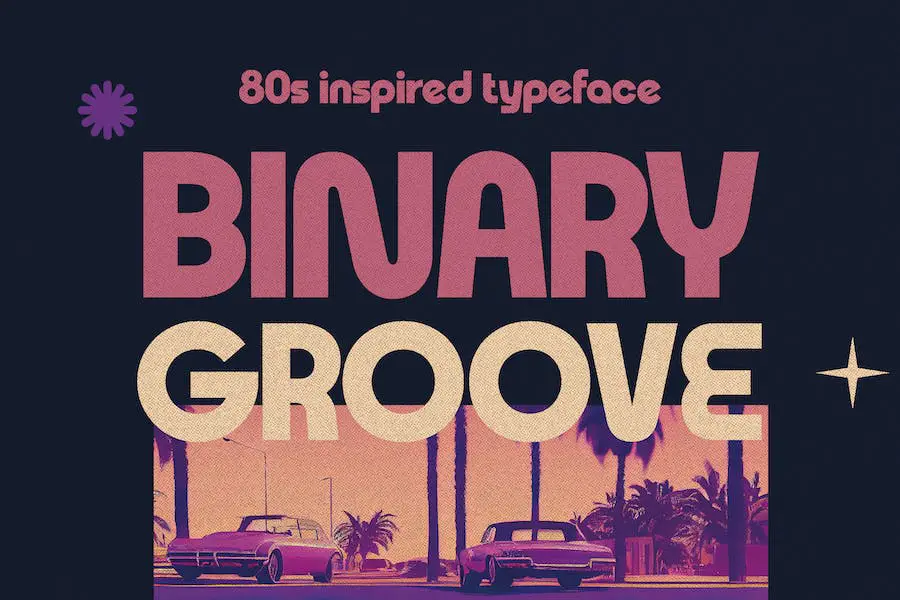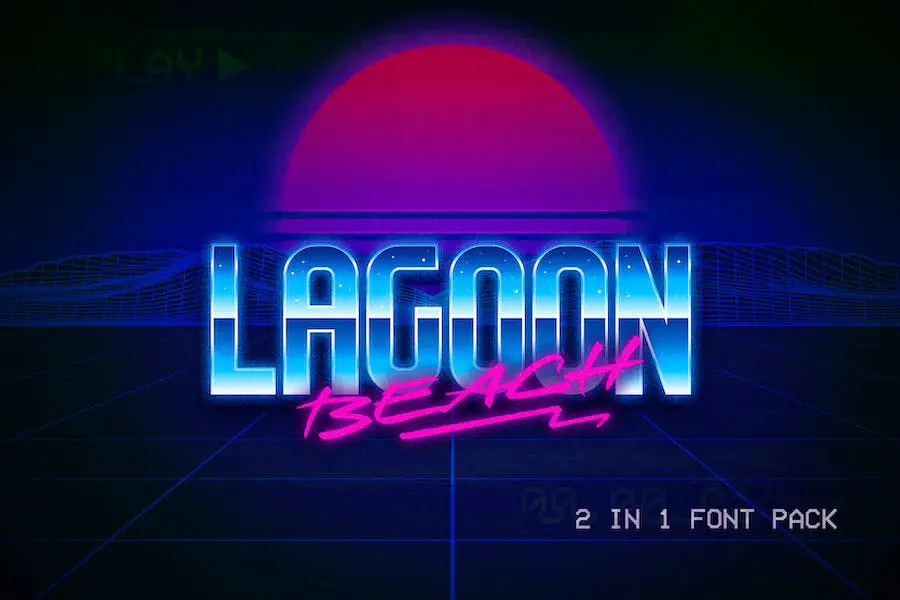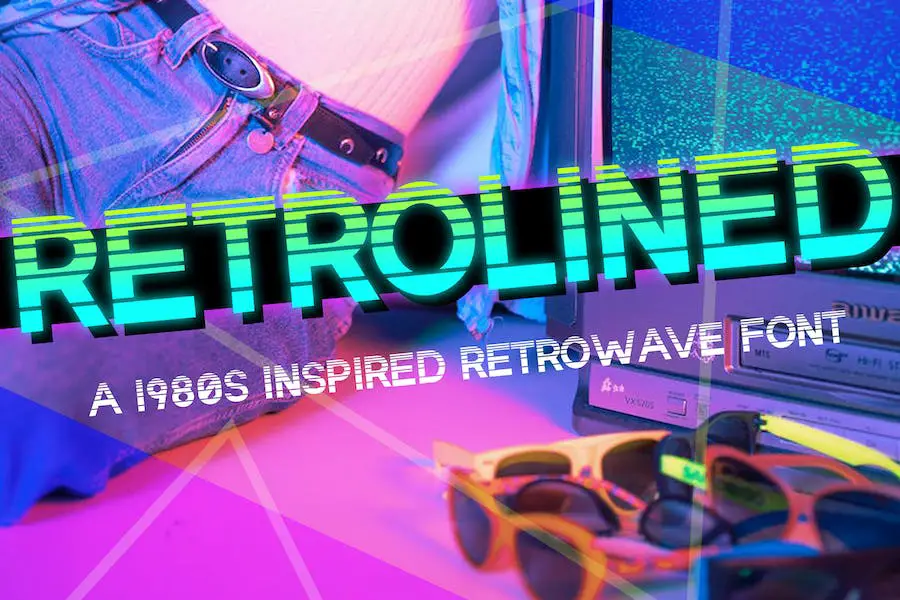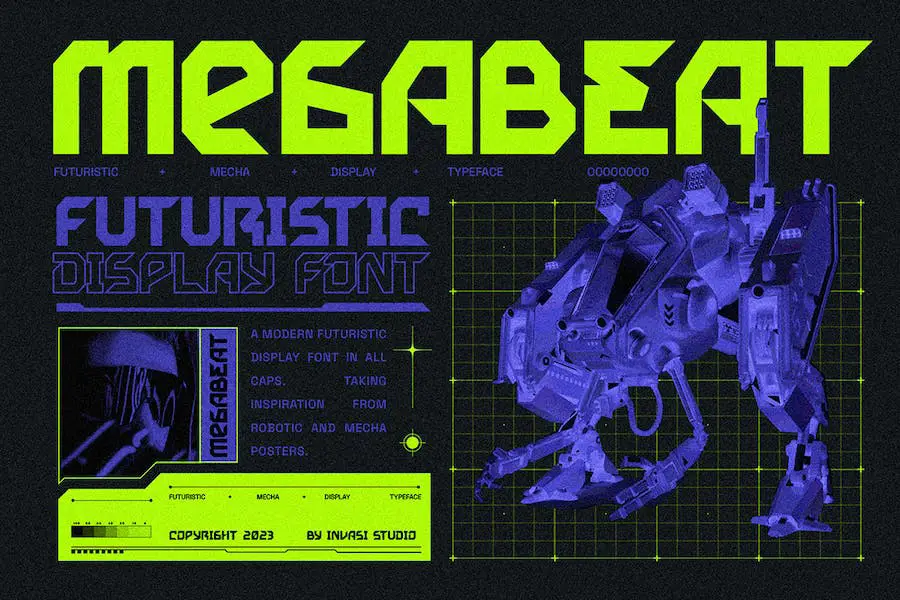
2023년 최고의 Vaporwave 글꼴 20개(무료 및 프리미엄)
게시 됨: 2023-09-06어떤 종류의 글꼴이 그래픽 디자인 프로젝트를 한 단계 더 발전시킬 수 있는지 궁금한 적이 있습니까? 더 이상 보지 마세요! 이 블로그 게시물에서는 프로젝트 디자인을 즉시 향상시킬 수 있는 최고의 증기파 글꼴 20가지를 살펴보겠습니다.
증기파란 정확히 무엇입니까? 베이퍼웨이브는 향수를 불러일으키는 80년대와 90년대의 미학으로 유명한 2010년대 초반에 시작된 음악 및 예술 장르입니다.
Vaporwave 글꼴은 대담하고 생생한 색상과 미래 지향적인 디자인으로 이 독특한 예술 형식의 본질을 포착합니다. 로고, 포스터, 웹사이트 등 어떤 작업을 하든 이러한 글꼴을 통합하면 프로젝트에 복고풍이면서도 현대적인 느낌을 줄 수 있습니다.
이제 증기파 글꼴의 세계로 뛰어들어 디자인을 변화시킬 상위 20가지 옵션을 살펴보겠습니다. 대담하고 기하학적인 글꼴부터 기발하고 몽환적인 글꼴까지 가장 인기 있고 시각적으로 매력적인 글꼴 목록을 선별했습니다.
이제 더 이상 고민하지 말고 여러분의 디자인 프로젝트를 다른 사람들보다 돋보이게 만들어 줄 글꼴을 찾아보세요.
최고의 프리미엄 Vaporwave 글꼴
그래픽 디자인 프로젝트를 향상시키고 싶으십니까? 우리가 엄선한 최고의 프리미엄 Vaporwave 글꼴 컬렉션을 만나보세요. 이 글꼴은 디자인에 독특하고 복고풍의 미학을 더해 다른 사람들보다 눈에 띄게 만들어줍니다.
최고의 글꼴을 탐색하고 실험할 수 있는 기회를 놓치지 마십시오. 귀하의 프로젝트를 한 단계 더 발전시켜줄 것입니다.
레트로퓨처리즘
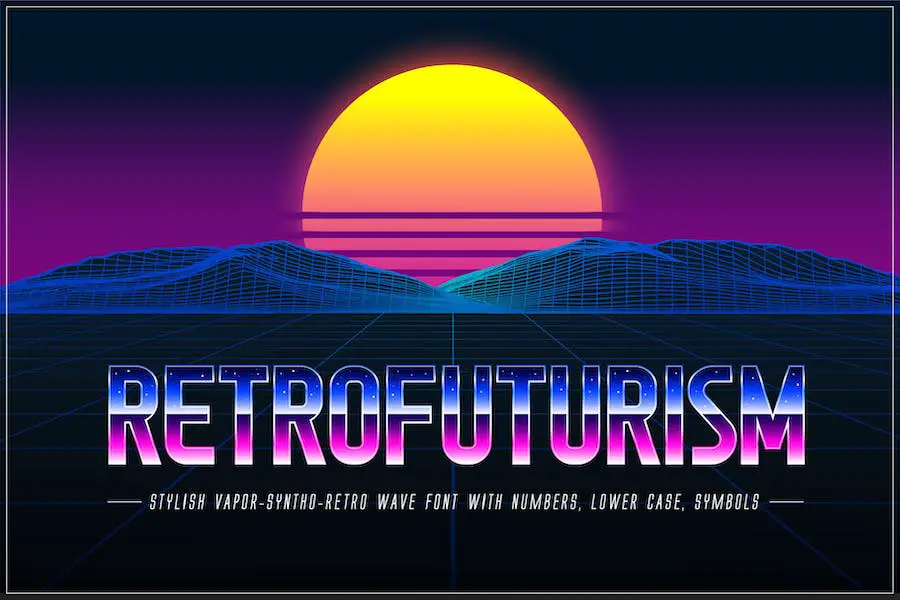
Retrofuturism은 Vaporwave, Synthwave 및 Retrowave 스타일의 복고풍 미래 지향적인 분위기를 프로젝트에 제공하는 멋지고 트렌디한 글꼴입니다.
독특하고 눈길을 사로잡는 미학을 갖춘 Retrofuturism은 향수와 미래 지향적인 감각으로 프로젝트를 향상시키려는 그래픽 디자이너에게 완벽한 선택입니다.
이 글꼴은 매우 다재다능하며 복고풍에서 영감을 받은 로고 및 브랜딩 제작부터 눈길을 끄는 포스터 및 소셜 미디어 그래픽 디자인에 이르기까지 다양한 디자인 목적으로 사용할 수 있습니다.
대담하고 역동적인 외관은 텍스트를 돋보이게 하고 시선을 사로잡아 디자인에 즉시 멋지고 복고풍적인 분위기를 더해줍니다.
증기미래주의
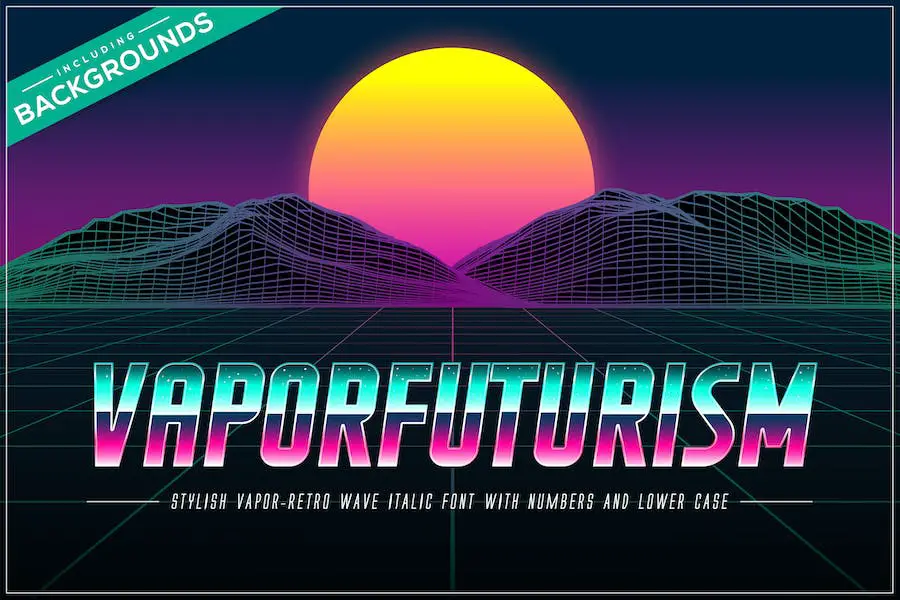
Vaporfuturism은 트렌디한 Vaporwave, Synthwave 및 Retrowave 스타일을 디자인에 적용하는 환상적인 글꼴 팩입니다.
하지만 그게 다가 아닙니다. 이 팩에는 추가 증기파 배경 4개와 샘플 전단지 2개가 포함되어 있습니다. 마치 하나의 패키지에 미니 디자인 키트가 들어있는 느낌이에요! 이러한 요소를 프로젝트에 통합하여 전반적인 미적 특성을 강화하고 눈에 띄게 만들 수 있습니다.
비디오 카세트
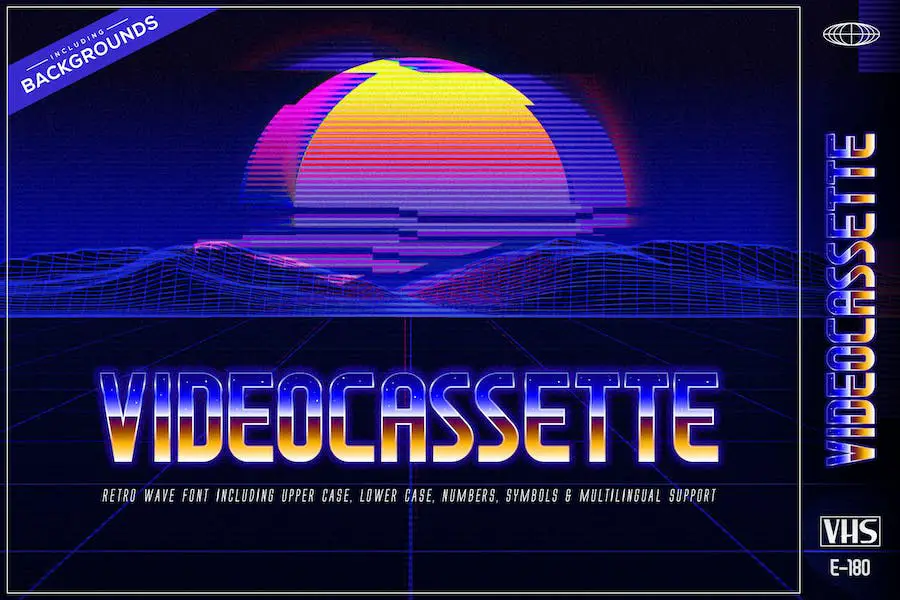
Videocassette는 팩에 포함된 80년대 Vaporwave 글꼴로 트렌디한 Vapor Wave, Synth Wave, Retro Wave 스타일이 특징입니다.
포스터, 앨범 표지, 웹사이트 디자인 등 어떤 작업을 하든 이 글꼴은 독특하고 눈길을 끄는 느낌을 더해 줄 것입니다. 다재다능함과 다양한 캐릭터 덕분에 다양한 목적에 적합하므로 매력적인 비주얼을 실험하고 만들 수 있습니다.
80년대 증기파 스타일의 본질을 포착하는 완벽한 글꼴인 Videocassette를 사용하여 프로젝트에 향수를 불러일으키는 느낌을 더해보세요.
레트로웨이브
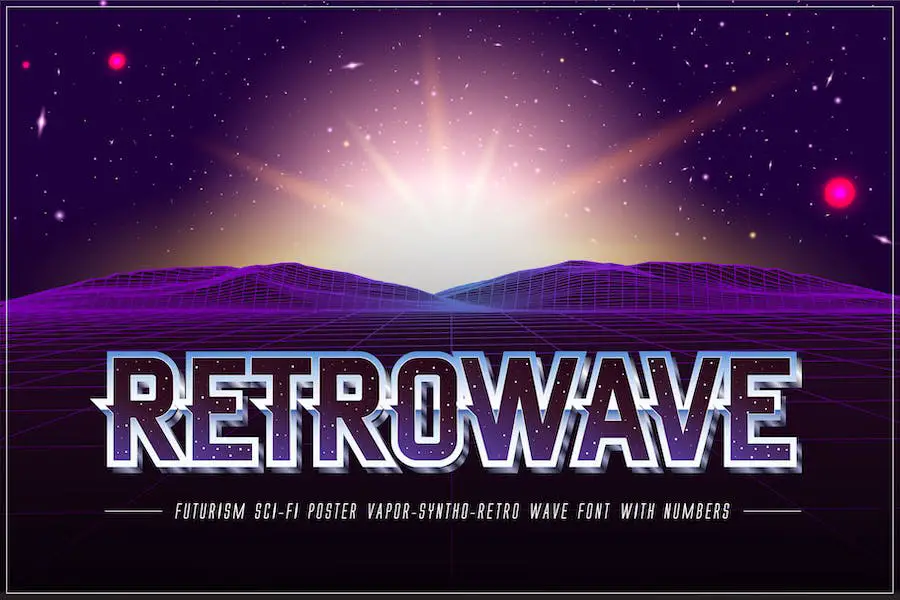
Retrowave는 트렌디한 Vaporwave, Synthwave 및 Retrowave 스타일을 제공하는 인상적인 글꼴 팩입니다. 다양한 색상의 OpenType 글꼴을 사용하여 모든 디자인 프로젝트에 활기차고 복고풍 느낌을 더해줍니다.
이 팩의 글꼴은 Vaporwave, Synthwave 및 Retrowave 장르의 멋지고 향수를 불러일으키는 미학의 전형을 보여줍니다. 각 캐릭터는 시대의 본질을 포착하고 프로젝트의 전반적인 디자인을 향상시키기 위해 세심하게 제작되었습니다.
Retrowave 글꼴 팩은 작업에 향수와 독창성을 추가하려는 그래픽 디자이너에게 적합합니다. 앨범 표지, 포스터, 소셜 미디어 그래픽 등 무엇을 만들든 이 글꼴은 디자인을 향상시키고 다른 사람들보다 돋보이게 만들어줍니다.
다양한 글꼴이 포함된 이 팩은 선택할 수 있는 다양한 옵션을 제공합니다. 각 글꼴에는 고유한 스타일이 있으므로 프로젝트에 딱 맞는 글꼴을 실험하고 찾을 수 있습니다. 대담하고 미래 지향적인 글꼴부터 우아하고 몽환적인 글꼴까지 모든 분위기와 분위기에 어울리는 글꼴이 있습니다.
라코네트
Lakonet은 독특하고 기발한 문자 형태를 특징으로 하는 디지털 디스플레이 글꼴로, 프로젝트의 디지털 컨셉을 향상시키는 데 적합합니다. 특별한 디자인은 어떤 디자인에도 창의성과 상상력을 더해줍니다.
글꼴의 문자 형태는 독특한 디지털 미학을 만들기 위해 신중하게 제작되었으므로 기술, 게임 디자인 및 미래 지향적인 테마와 관련된 프로젝트에 이상적입니다. Lakonet의 파격적인 스타일은 디자인에 신선하고 유쾌한 분위기를 더해 보는 사람의 관심을 사로잡습니다.
Lakonet은 특별한 속성을 통해 시장의 다른 글꼴 중에서 단연 돋보입니다. 디지털 디스플레이 스타일은 시선을 사로잡고 시선을 사로잡기 때문에 헤드라인, 로고 및 포스터에 적합한 선택입니다.
웹사이트, 디지털 광고, 소셜 미디어 그래픽 등 어떤 작업을 하든 Lakonet은 전반적인 디자인을 향상시키고 시각적 효과를 향상시킬 수 있습니다. 글꼴의 고유한 특성으로 인해 다양한 프로젝트에서 다양한 선택을 할 수 있어 놀라운 시각적 효과를 실험하고 만들 수 있습니다.
오버드라이브 애비뉴
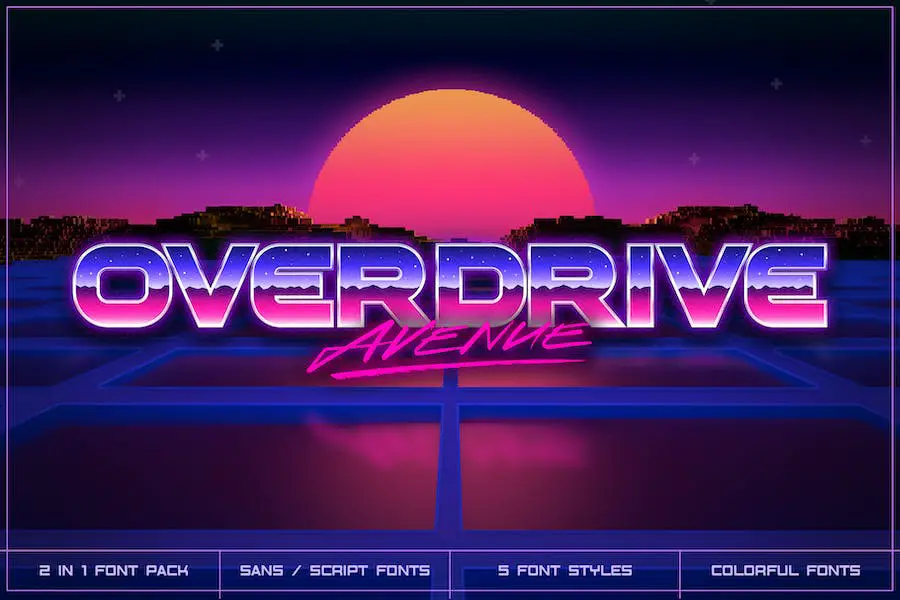
Overdrive Avenue는 여러분을 80년대와 90년대 초반의 향수를 불러일으키는 시대로 데려다줄 글꼴입니다.
Sans 스타일과 Script 스타일을 모두 2-in-1로 제공하고 총 5가지 스타일 중에서 선택할 수 있는 이 글꼴은 기억에 남는 시대의 분위기를 재현하는 데 적합합니다.
Retro wave를 염두에 두고 디자인된 Overdrive Avenue는 .OTF 형식으로 제공되는 Color OpenType 글꼴로, Adobe Illustrator 및 Photoshop 2018 이상 버전과 호환됩니다.
Overdrive Avenue를 사용하면 80년대와 90년대의 매력과 따뜻함을 쉽게 되살릴 수 있습니다. 향수를 불러일으키는 프로젝트를 진행 중이거나 단순히 소중한 추억을 불러일으키고 싶은 경우에도 이 글꼴이 도움이 될 것입니다.
Sans 및 Script 스타일을 모두 제공하는 다용성 덕분에 자유롭게 실험하고 디자인에 딱 맞는 스타일을 찾을 수 있습니다.
Overdrive Avenue의 Sans 스타일은 깨끗하고 매끄럽고 그 시대에 유행했던 미래 지향적인 미학을 연상시킵니다. 레트로한 느낌에 모던한 느낌을 더해 다양한 디자인 용도로 활용하기 좋습니다.
반면에 스크립트 스타일은 프로젝트에 손으로 직접 쓴 듯한 느낌을 줍니다. 개인적인 느낌을 더해주며 타이포그래피 중심 디자인에 잘 어울립니다.
영원히 뛰어넘어라
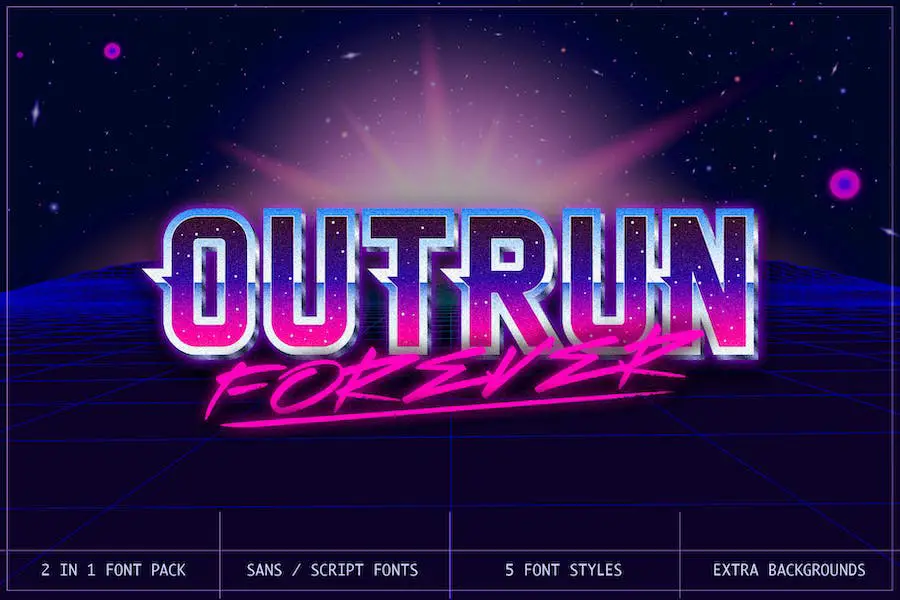
Outrun Forever는 It이라는 향수를 불러일으키는 2-in-1 글꼴입니다. 여기에는 Sans 및 Script 스타일이 모두 포함되어 있으며 선택할 수 있는 총 5가지 스타일이 있습니다.
Outrun Forever를 사용하면 우리 모두가 사랑하고 머릿속에 상상하는 80년대 분위기에 맞는 완벽한 분위기를 쉽게 만들어 따뜻하고 소중한 추억을 불러일으킬 수 있습니다. 복고풍 향수를 가미하여 프로젝트를 향상시키려는 그래픽 디자이너에게 이상적인 글꼴입니다.
Outrun Forever는 디자인을 향상시킬 수 있는 증기파 글꼴을 찾는 Canva 사용자에게 탁월한 선택입니다. 독특한 스타일과 향수를 불러일으키는 느낌은 모든 프로젝트에 독특하고 매혹적인 미학을 더할 것입니다.
소셜 미디어 게시물, 웹사이트 배너, 브랜딩 자료 등 어떤 작업을 하든 Outrun Forever는 다양한 디자인 요구 사항에 맞는 다용성을 갖추고 있습니다.
Cricut 사용자의 경우 Outrun Forever는 제작 프로젝트를 한 단계 더 발전시키는 데 꼭 필요한 글꼴입니다. 복고풍 스타일은 비닐 데칼, 전사 전사 제품 및 맞춤 선물에 독특하고 눈길을 끄는 터치를 더해줍니다.
Outrun Forever를 사용하면 대중들 사이에서 눈에 띄고 지속적인 인상을 남길 수 있는 맞춤형 디자인을 쉽게 만들 수 있습니다.
제목, 제목 또는 시각적으로 눈에 띄게 만들고 싶은 텍스트에 증기파 글꼴을 사용하여 디자인에 통합할 수 있습니다. 이 글꼴은 디지털 아트워크, 앨범 표지, 포스터 및 소셜 미디어 그래픽에서 잘 작동합니다.
단지 그것들을 아껴서 사용하고 디자인의 전반적인 미학을 보완하도록 주의하세요.
결론
결론적으로 우리는 프로젝트 디자인을 향상시키려는 그래픽 디자이너에게 완벽한 상위 20개 증기파 글꼴을 탐색했습니다. 우리는 각 글꼴의 고유한 특성과 이를 통해 디자인을 새로운 차원으로 끌어올릴 수 있는 방법에 대해 논의했습니다.